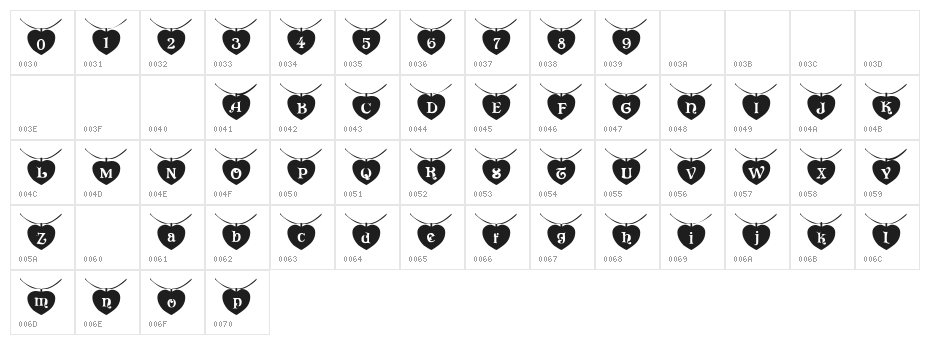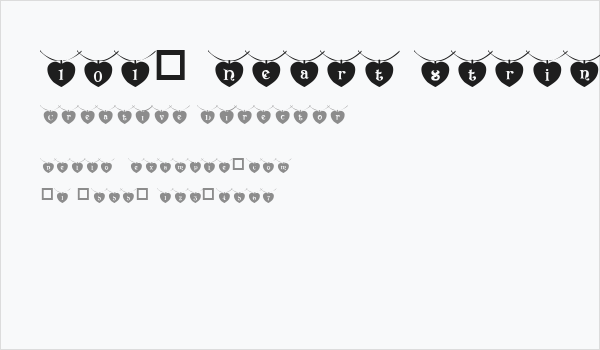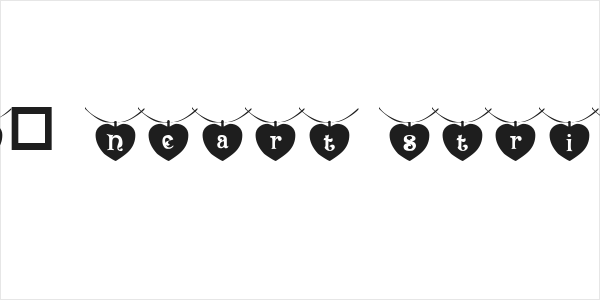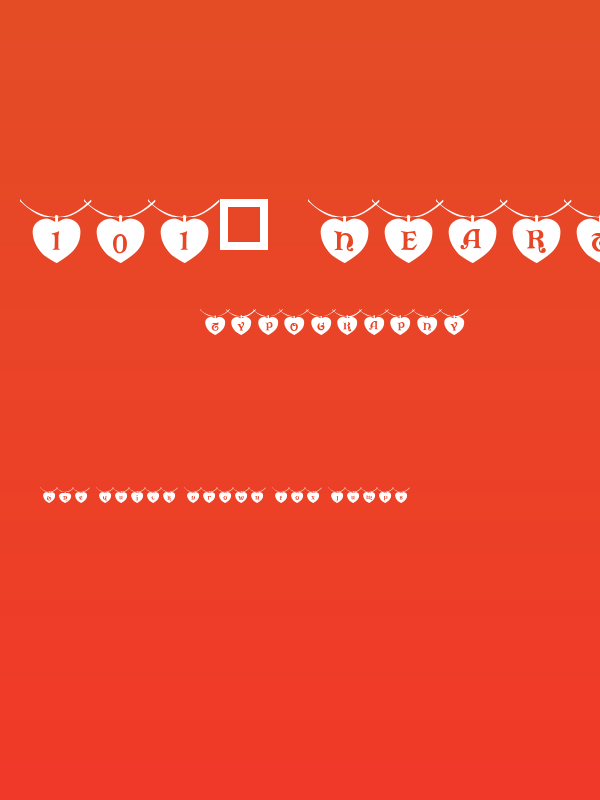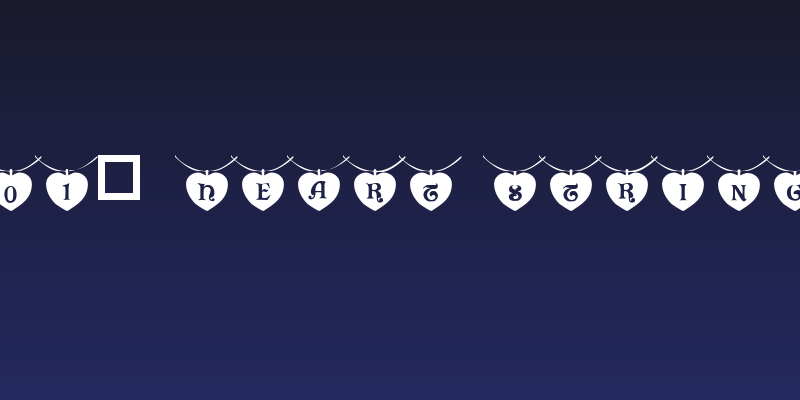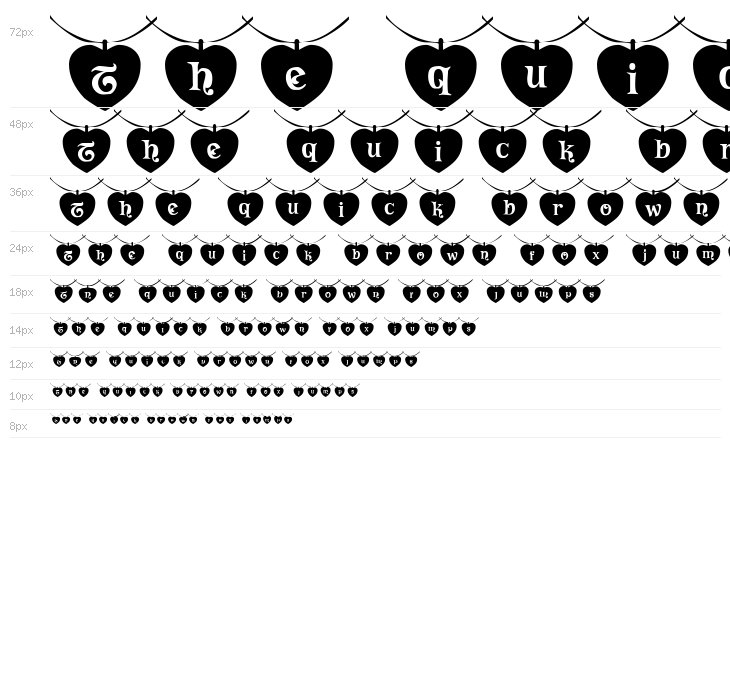
101! Heart StringZ Font
| Caso d'uso | Headlines, Logos, Decorative text |
| Progetti proposti | Ideal for Valentine's Day cards, wedding invitations, romantic banners, festive decorations, and playful branding projects. |